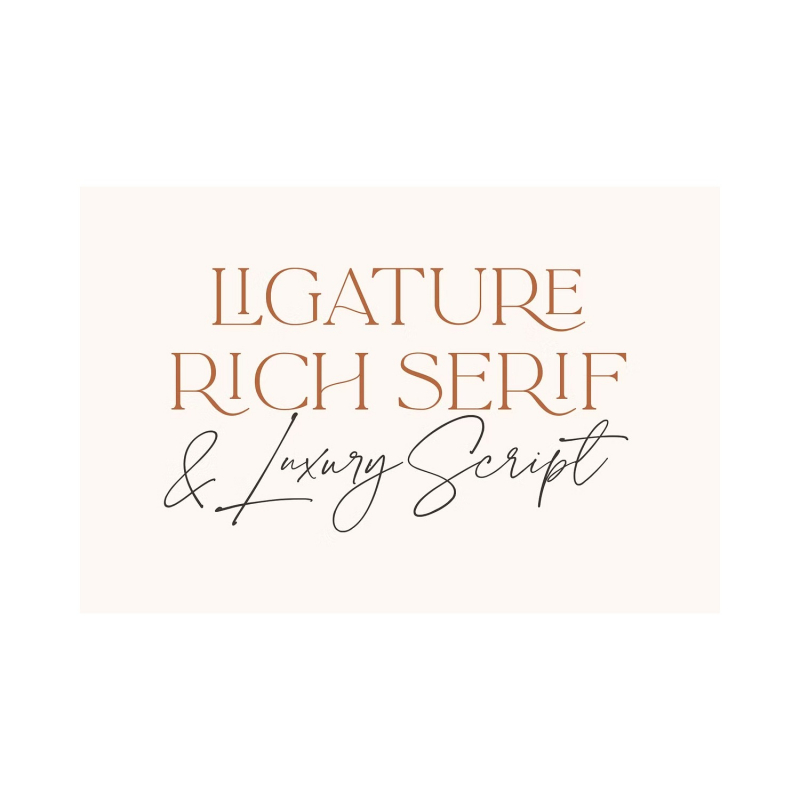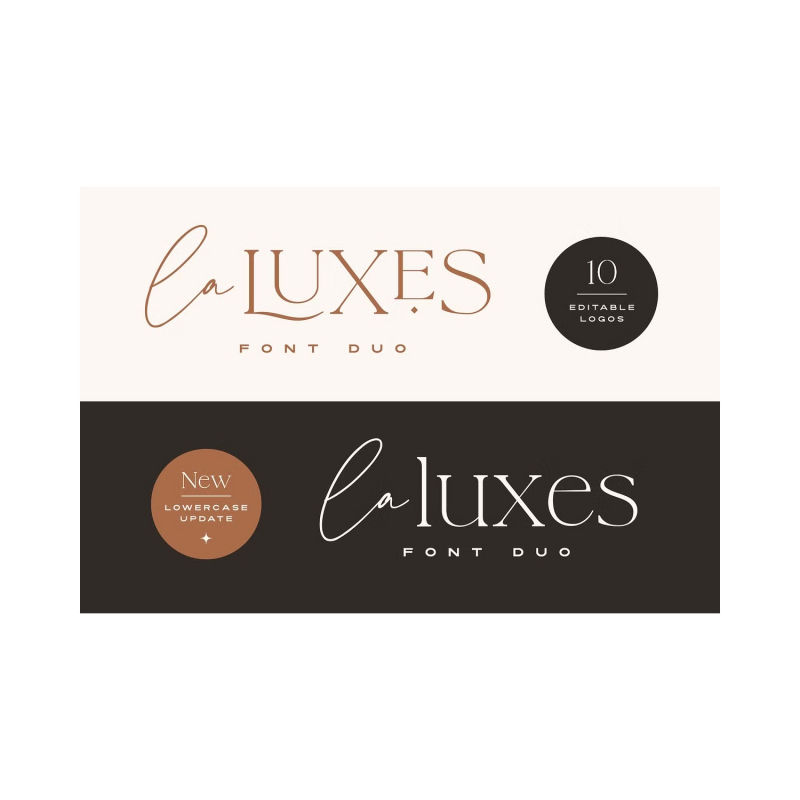
La Luxes الخط الثنائي + الشعارات (محدث!)
دلل نفسك في الطباعة الفاخرة مع La Luxes. ثنائي خط كلاسيكي يتكون من نص أنيق و Serif غني بالأحرف المركبة. يتضمن هذا المنتج أيضا 10 قوالب شعار إضافية ، مما يتيح لك تحرير التصميمات التي تراها في الصور أعلاه بسهولة وإنشاء شعارات مذهلة في دقائق. (تتطلب قوالب الشعار فتح Adobe Photoshop أو Adobe Illustrator).
• La Luxes Script • خط نصي نظيف وأنيق مرسوم باليد يحتوي على أحرف كبيرة وصغيرة ، وجميع علامات الترقيم والأرقام. يحتوي أيضا على 30 حرفا مركبا للمساعدة في تدفق النص بشكل طبيعي وإضافة إحساس مخصص.
• La Luxes Serif • حرف أنيق وعصري يحتوي على أحرف كبيرة وأحرف صغيرة جديدة ، وجميع علامات الترقيم والأرقام. يحتوي أيضا على 38 حرفا مركبا و 11 حرفا خاصا مما يمنحك مجموعة متنوعة من خيارات التخطيط.
• 10 قوالب شعار • يتم أيضا تضمين تصميمات الشعار العشرة الموضحة في الصور أعلاه كملفات شعار قابلة للتحرير. ما عليك سوى فتح أي من القوالب باستخدام Photoshop أو Illustrator ، وتحرير النص واختيار الألوان الخاصة بك إذا كنت ترغب في ذلك. الشعارات متجهة بالكامل ويمكن تحجيمها إلى أي حجم دون فقدان الجودة.